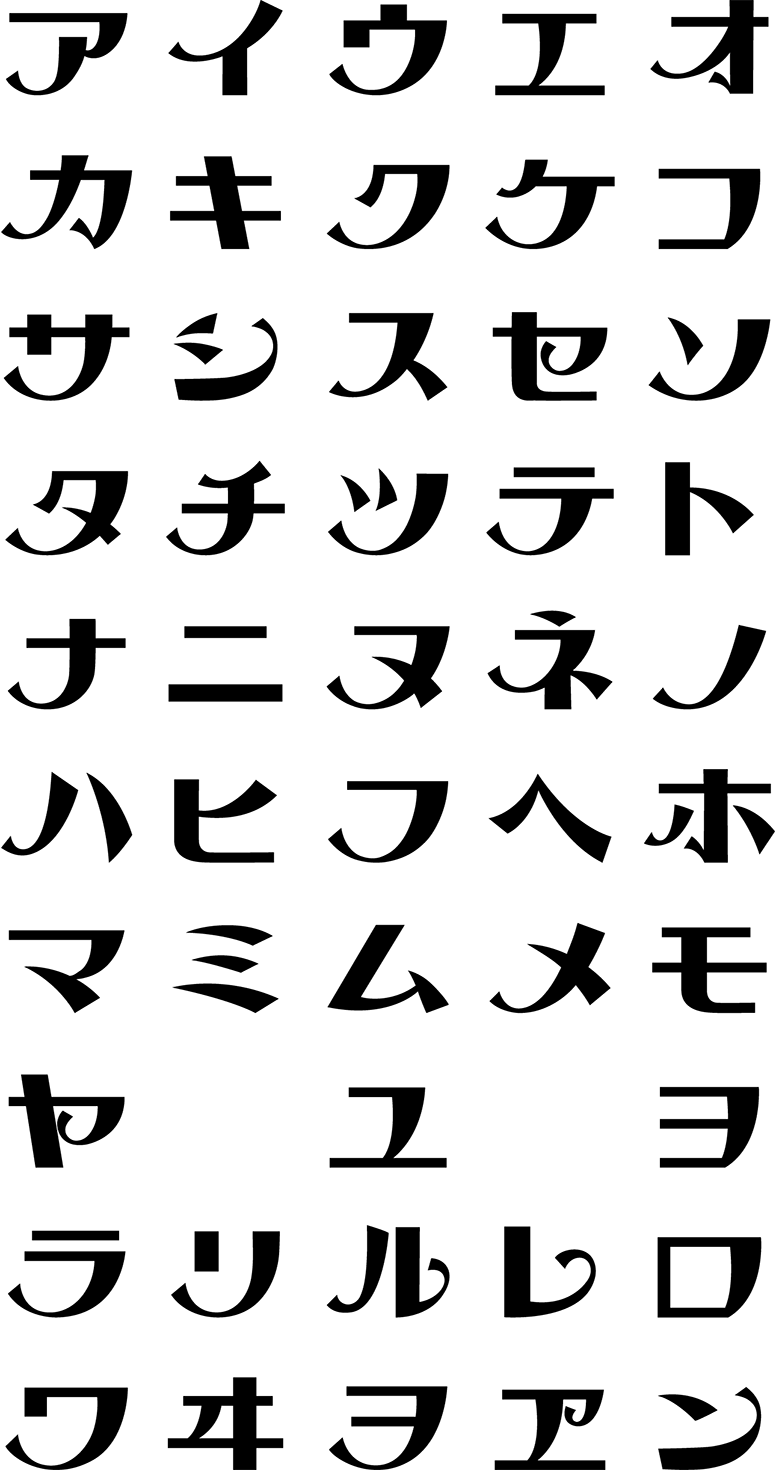
Виды японских шрифтов, как установить японскую раскладку клавиатуры
Здравствуйте, дорогие читатели! Хочу с вами сегодня поговорить о японской письменности, о существующих системах японского письма, а также о японских шрифтах для компьютера и о том, как установить японскую раскладку клавиатуры.
На данный момент в японском языке можно выделить три системы письменности: к первой относятся кандзи, в основе которой лежат китайские иероглифы, вторая и третья — это слоговые азбуки катакана и хирагана. Все эти три системы вместе называются «кандзи-кана-мадзирибун»(漢字仮名交じり文), то есть смешанное использование иероглифов и азбук — каны.
Также существует четвёртая особая система — транслитерация японских символов латиницей. Это ромадзи.
Поговорим о каждой из систем и их краткой истории в отдельности.
Кандзи (漢字) — система письменности, которая пришла из Китая. Ее название буквально переводится как “буквы [династии] Хань”. Первые иероглифические тексты связаны с монахами-буддистами и появились в Японии в V веке.
Отличительной чертой кандзи является то, что иероглифы могут иметь несколько вариантов чтения (у некоторых кандзи доходит даже до 10), а также исключения. Какой именно вариант чтения используется, определяется местом иероглифа в слове, предложении и тем, как он сочетается с другим иероглифом в контексте.
В современном языке минимальный набор кандзи, который изучается в школах, 2136 знаков.
Рассмотрим далее две слоговые азбуки, которые произошли от кандзи и являются упрощённым вариантом их начертания.
Хирагана (平仮名) — слоговая азбука, состоящая из символов-слогов. Хираганой часто пользуются, когда предполагается, что читающий или пишущий текст не знает каких-либо иероглифов, ею подписывают знаки фуриганы (чтение иероглифов). Эта азбука также используется для записи окончаний глаголов, прилагательных (которые изменяются в процессе речи в зависимости от грамматики).
В манъёгане китайским иероглифам ставилось в соответствие японское произношение.Интересный факт: изначально хираганой пользовались только женщины без надлежащего уровня образования. Сейчас тексты, записанные хираганой, можно встретить разве только в детских книжках и в учебниках для начинающих учить японский язык.
Катакана разработана также из манъёганы буддийскими монахами, только символы этой азбуки более угловаты и просты. Катакану используют для того, чтобы записывать слова иностранного происхождения, часто не имеющие аналога в написании иероглифами.
И, наконец, система ромадзи — запись японских слов латинскими символами, которая ведёт свою историю ещё с середины 16-го века, когда японские католики разработали первую систему латинизации японской письменности, приняв за основу португальский язык.
Некоторые шрифты доступны только для английского языка, другие — также для русского языка. Если вдруг вам понадобиться оформить афишу для мероприятия или пост для личной страницы в социальных сетях, теперь можно не ломать голову о том, как же записать буквы русского алфавита в японском стиле. Компьютер сделает это за вас 🙂
Среди представленных шрифтов также есть те, что предназначены для японского языка.
Виды японских шрифтов, как установить японскую раскладку клавиатуры — обо всем этом рассказываем в нашей статье. Где скачать шрифт в стиле японских иероглифов?